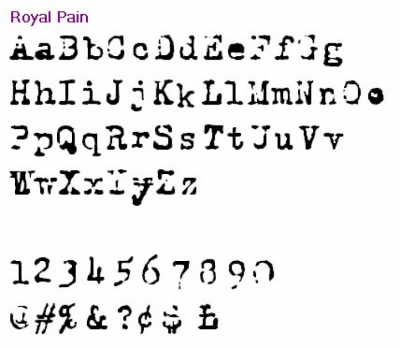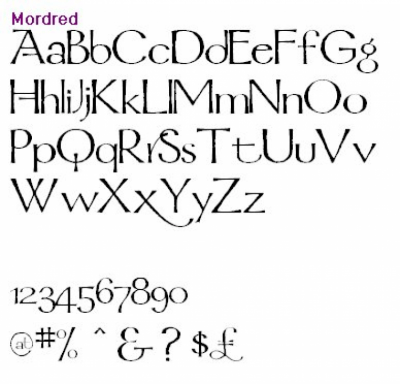
Artistic Font Collection
Artistic Font Collection Большая бесплатная коллекция разнообразных шрифтов, в которой каждый пользователь найдет то, что ему нравится. С ее помощью вы сможете придать Mac OS красивый, элегантный и изысканный вид.